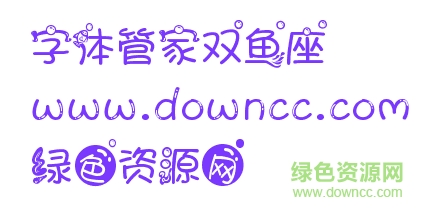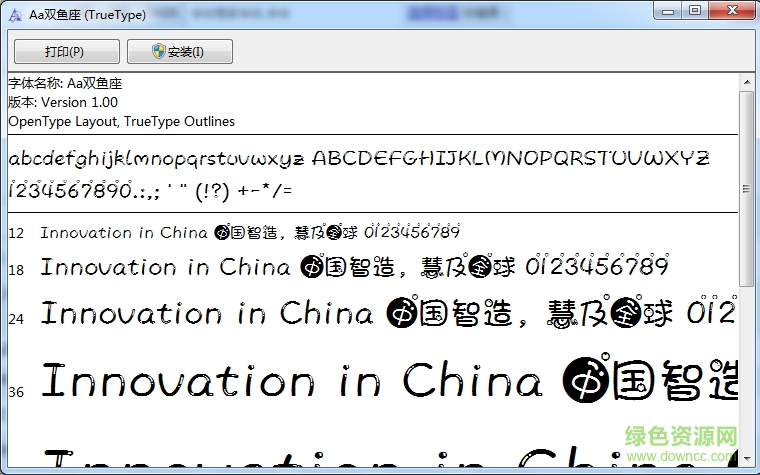
aa雙魚座字體是一款活潑生動(dòng)的字體管家字體,有著可愛的氣泡點(diǎn)綴,部分漢字更是直接被泡泡圈起,還有黑白相間的設(shè)計(jì),讓字體更有獨(dú)特的韻味,如果您也喜歡,就來綠色資源網(wǎng)免費(fèi)體驗(yàn)吧!
字體管家雙魚座字體是一款用于星座設(shè)計(jì)方面的字體,整體字形筆畫均衡,在字體間嵌入卡通圖案。字體與圖案相結(jié)合就要?jiǎng)?chuàng)意性,又很有趣味性,特別適合喜歡字體個(gè)性一些的朋友在安裝使用。本作品適用于泡泡設(shè)計(jì)字體、創(chuàng)意設(shè)計(jì)字體、藝術(shù)設(shè)計(jì)字體、星座設(shè)計(jì)字體。
字體管家雙魚座是一款以POP體為原形進(jìn)行裝飾的卡通字體,字體間裝飾了有趣的卡通圖案,趣味性十足!